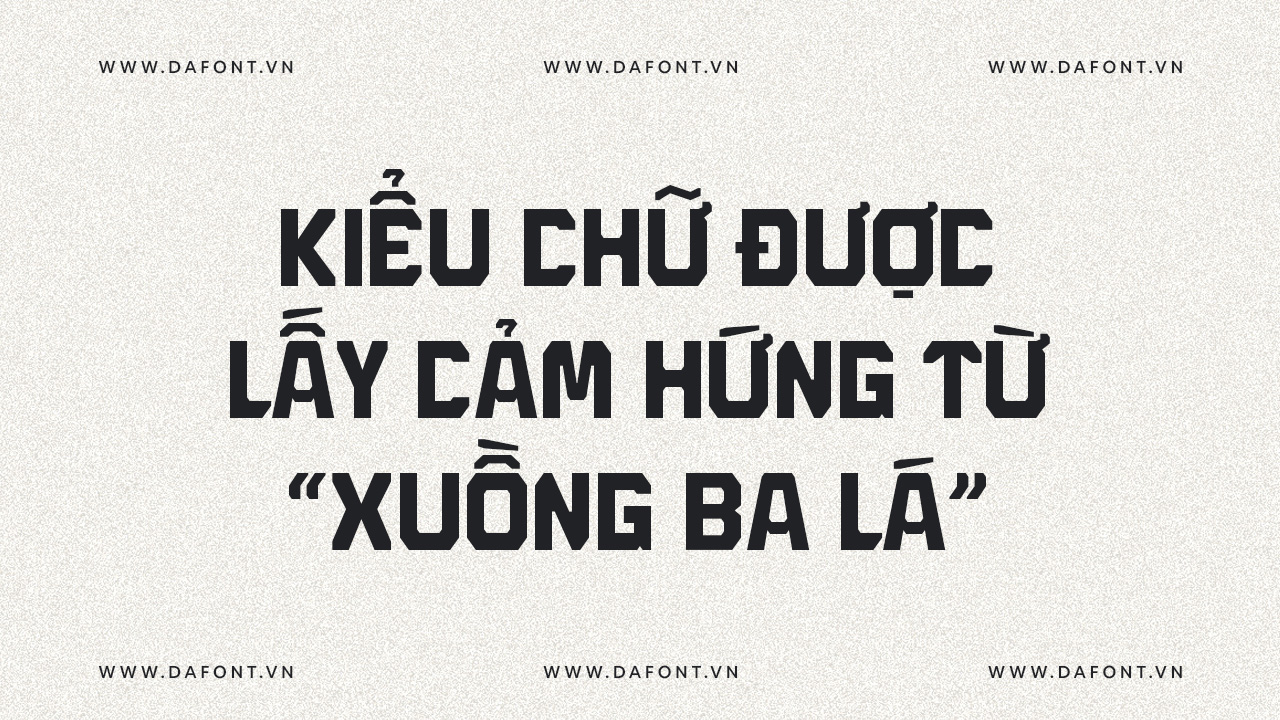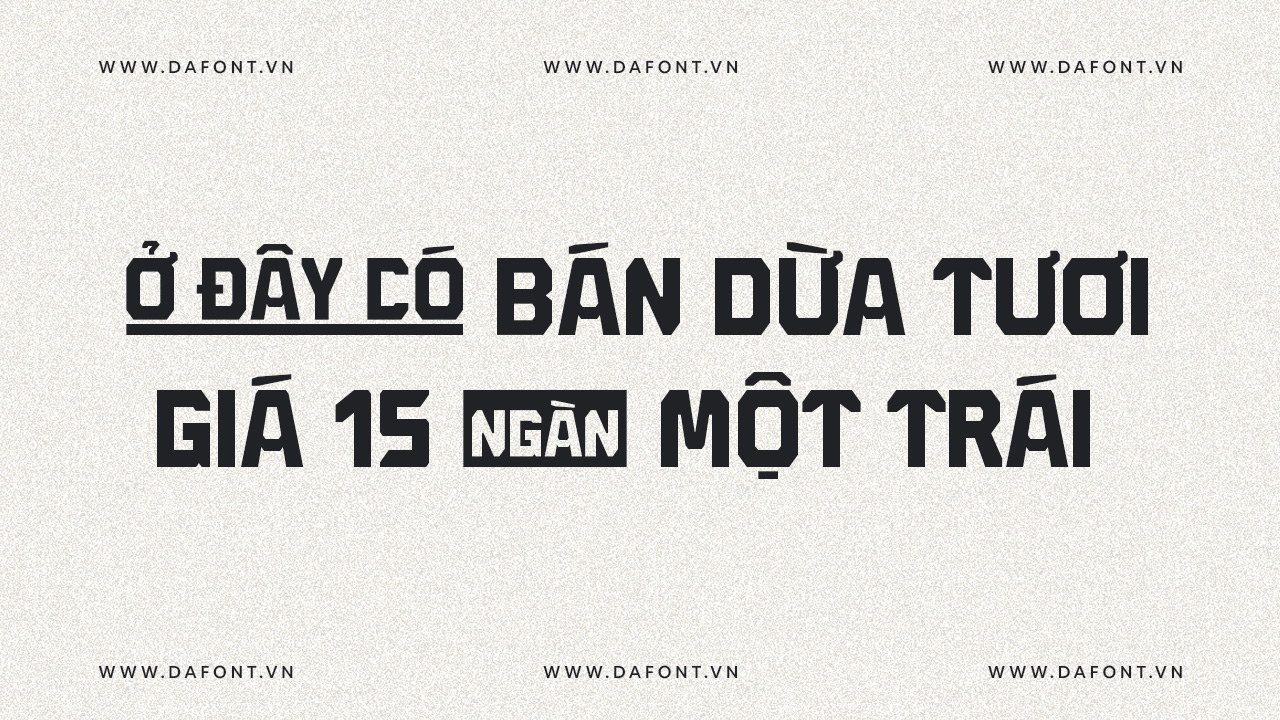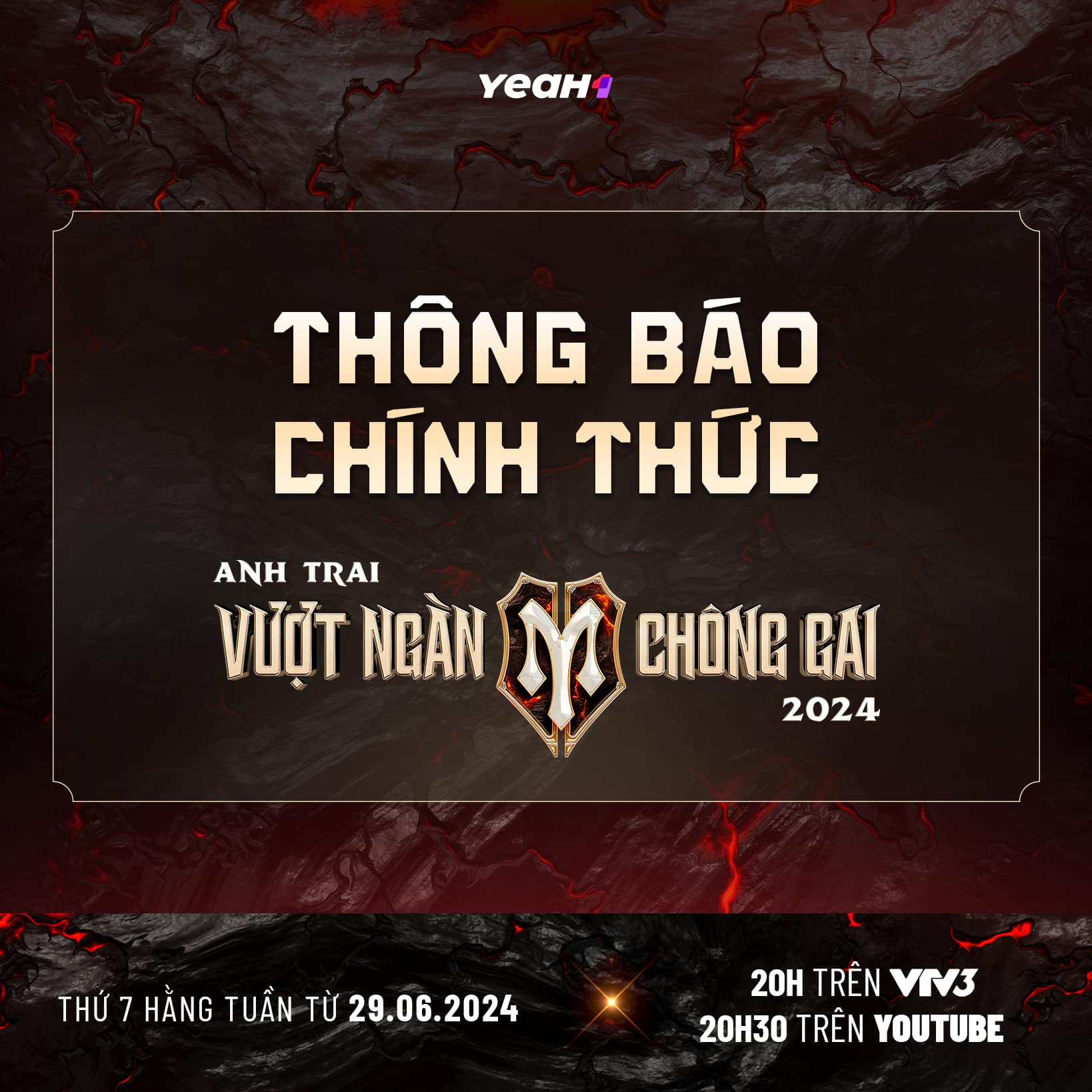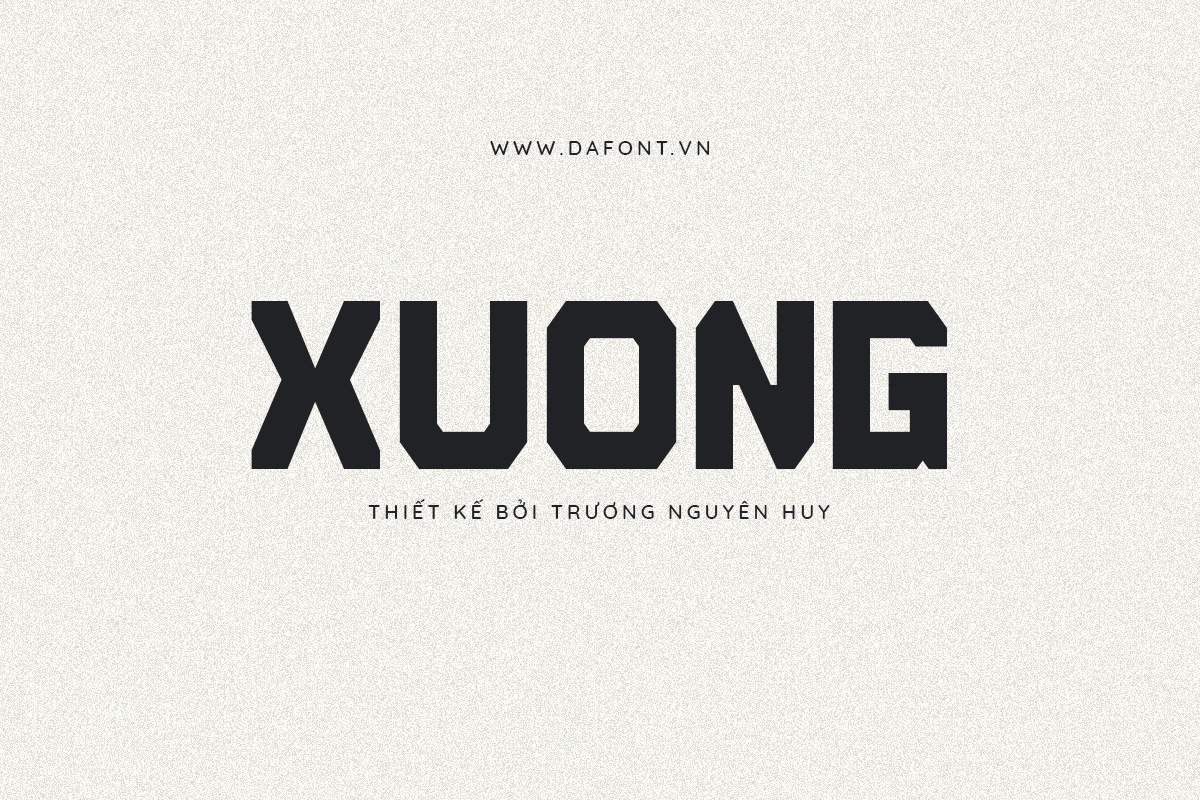
Xuong Display Typeface font chữ được thiết kế bởi Trương Nguyên Huy. Kiểu chữ được lấy cảm hứng từ “Xuồng Ba Lá”, một trong những phương tiện di chuyển trên sông của người dân miền Tây Nam Bộ.
Xuồng Ba Lá là chiếc thuyền nhỏ di chuyển trên các con sông ở các tỉnh miền Tây Nam Bộ, được đóng bằng ba mảnh ván phẳng, đẹp và chắc chắn. Một mảnh rộng (to bản) hơn được dùng làm đáy xuồng. Hai mảnh hai bên làm mạn xuồng, địa phương gọi là be xuồng.
Chính vì những đặc điểm của nó mà Xuong Display Typeface được ra đời, những nét chữ chắc chắn tượng trưng cho những tấm ván gỗ được nối lại với nhau. Bên cạnh đó, các ký tự thể hiện sự chắc chắn, mang lại cảm giác thủ công tương tự như quá trình sản xuất Xuồng Ba Lá.
Đây là kiểu chữ All Caps vì vậy nó phù hợp để sử dụng làm hiển thị và trang trí. Font được sử dụng miễn phí cho mục đích cá nhân và thương mại.
Ngoài ra, đây là kiểu chữ được sử dụng trong chương trình Anh trai vượt ngày chông gai đang tạo nên làn sóng ủng hộ rất lớn từ phía khán giả.
Xuong Display Typeface còn bao gồm một số chữ ghép, bạn có thể sử dụng nó qua bảng Glyph trên PTS hoặc AI.